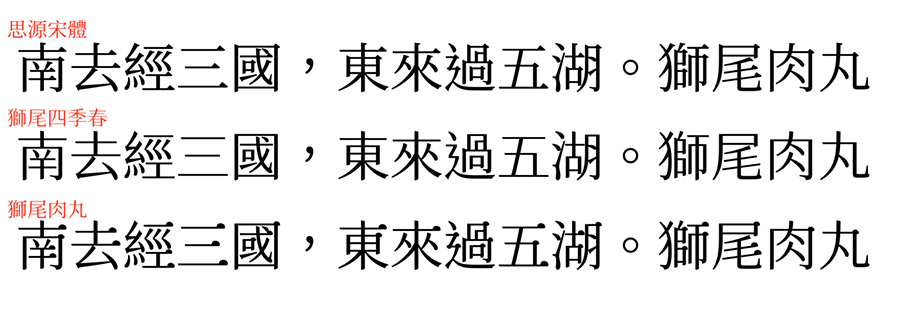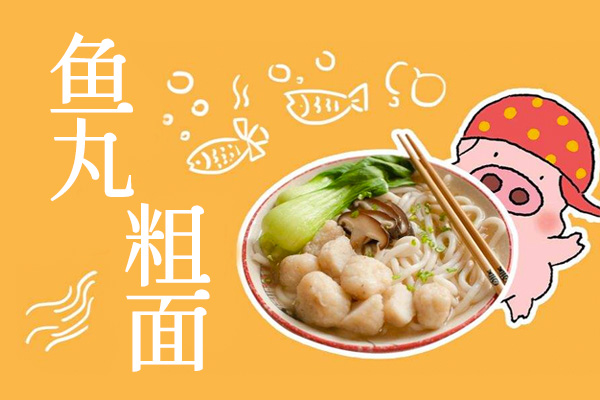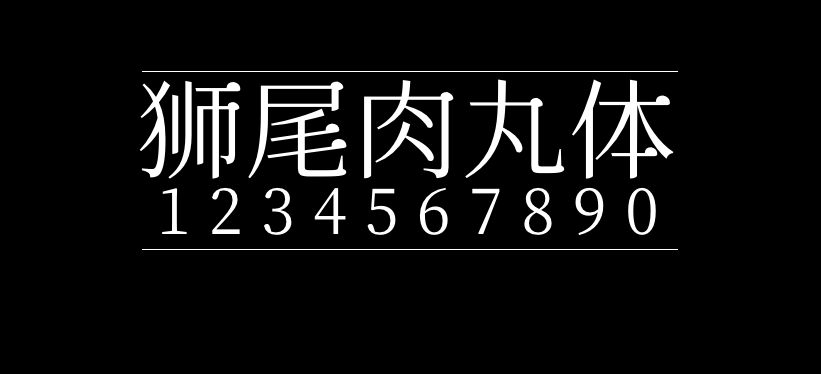
狮尾肉丸体
狮尾肉丸体(Swei Meatball CJK TC)是台湾的字体设计师MAX基于思源宋体进行修改,创造的一款新字体。将思源宋体字形中的三角形替换半圆形改造而成,是一款更加简明现代化的字体。支持简体中文、繁体中文、韩文与日文;和思源宋体一样,狮尾肉丸体拥有7个字重,能满足大部分的设计需求。
把电脑书法字体常见的三角形改成圆形。在日本已经有类似的可爱字体,很多细节日本字体做的比较细致,日本字体常见的缺点在汉字比常见中文字少很多,很容易缺字,而且日文汉字有些笔顺跟中文不太一样。
相比于思源宋体,狮尾肉丸的造型更加简明现代,版面效果清新轻快。狮尾肉丸体是基于思源系列字体改造而成,使用的是人工智能程式批量进行处理的,所以拥有思源字体的超大字符集,简体和繁体都基本上不缺字。